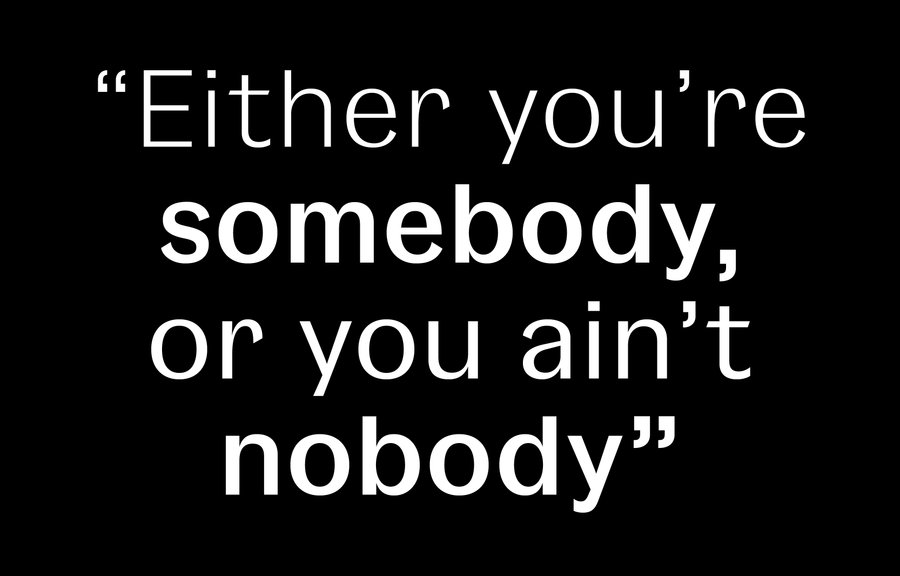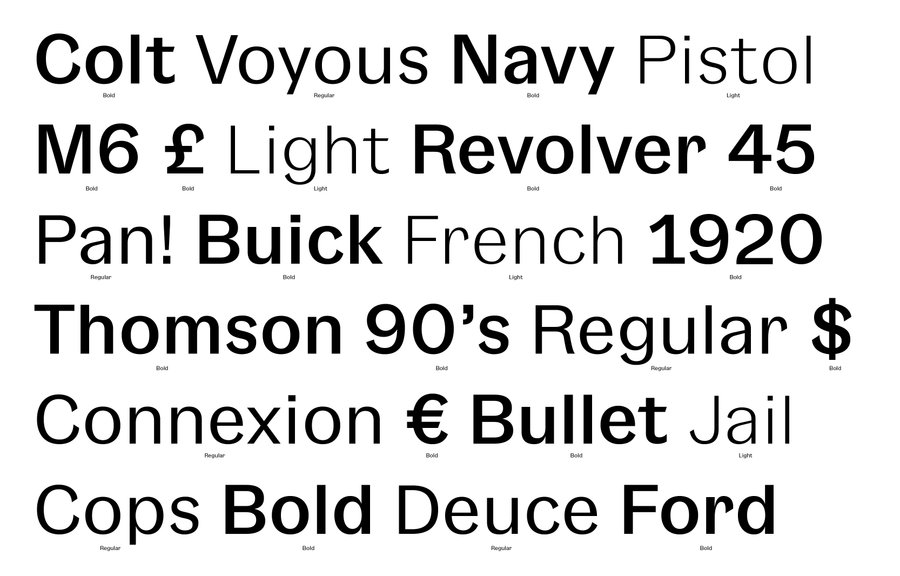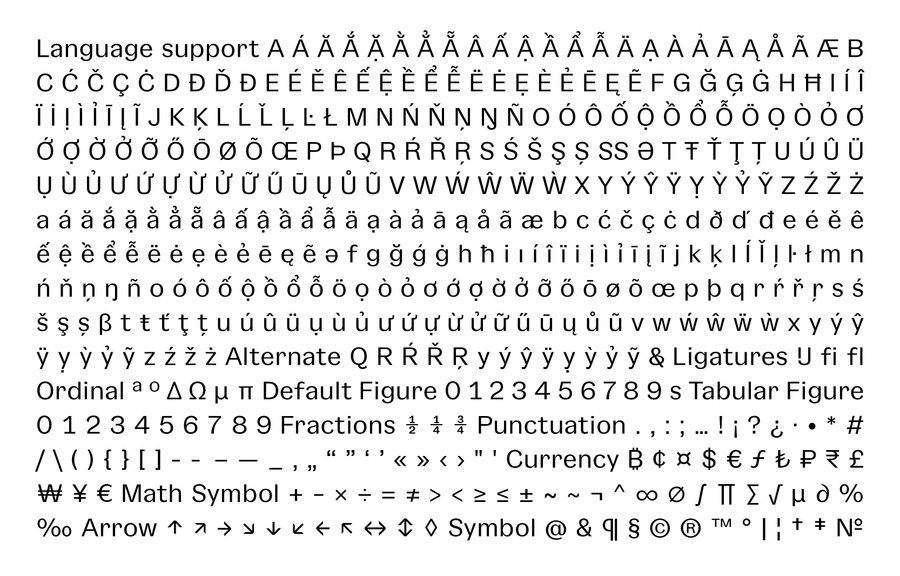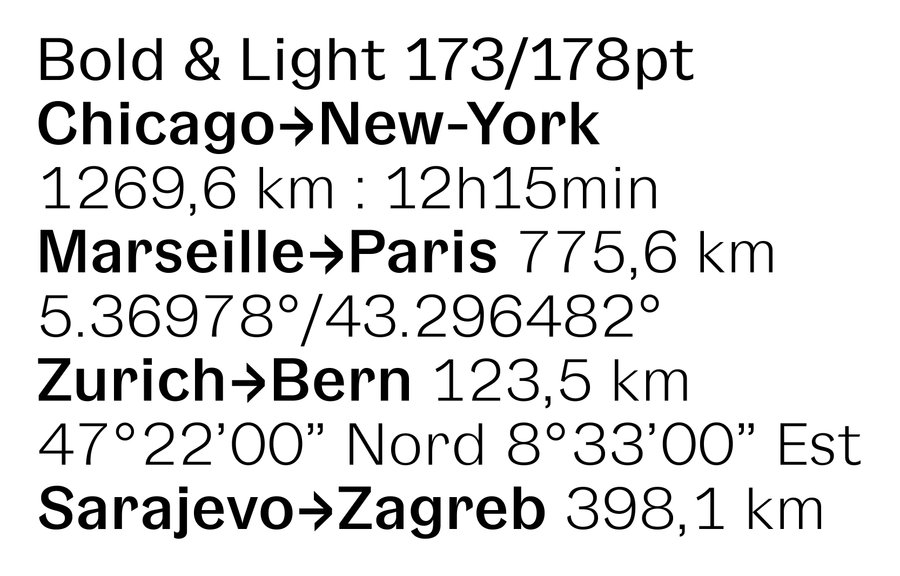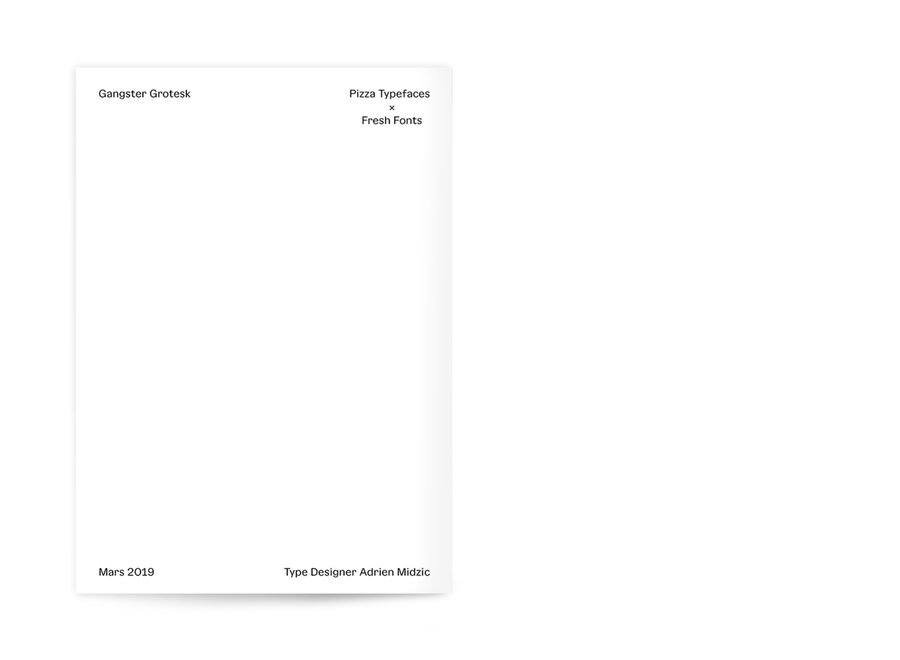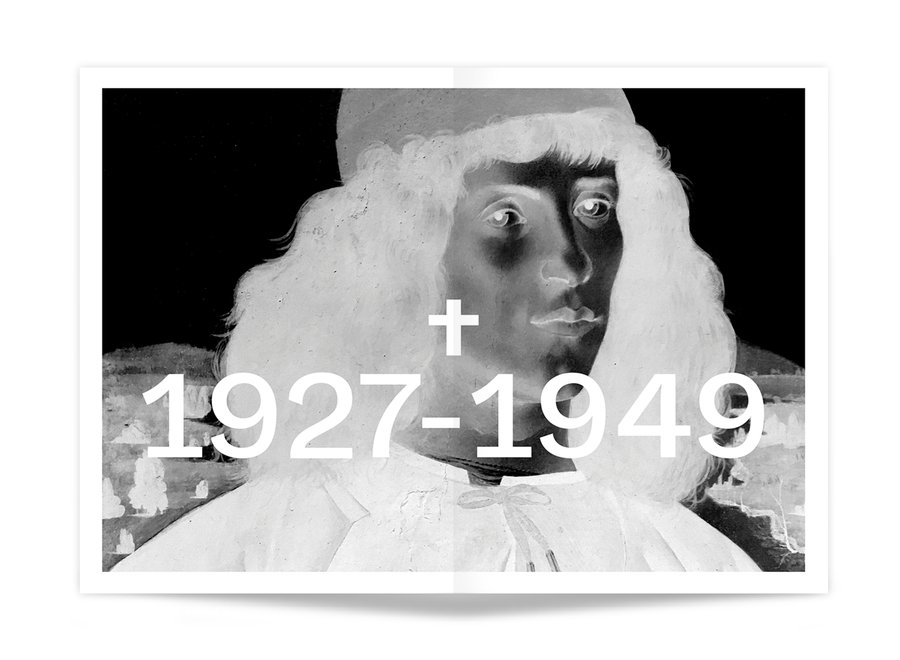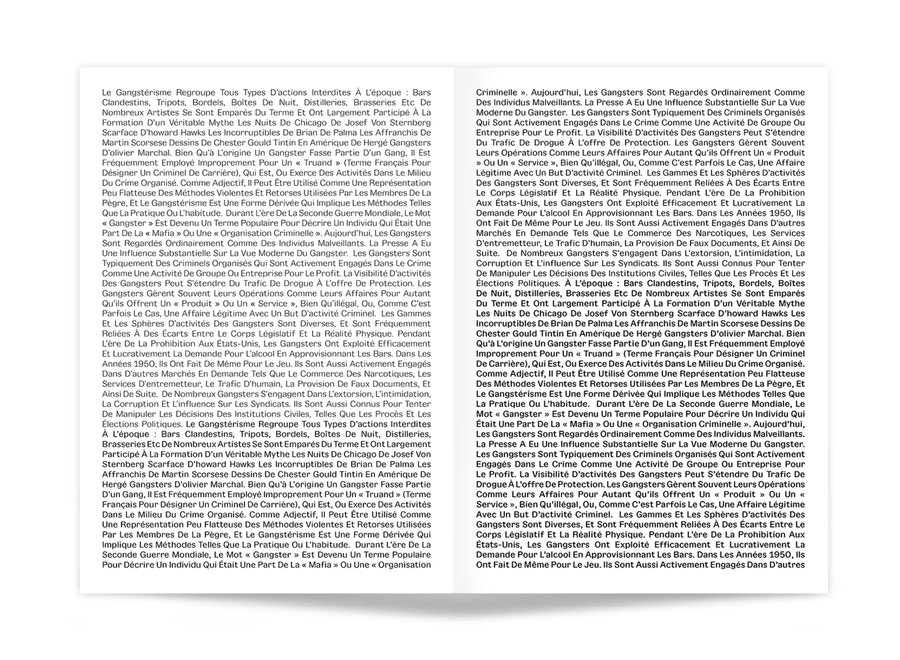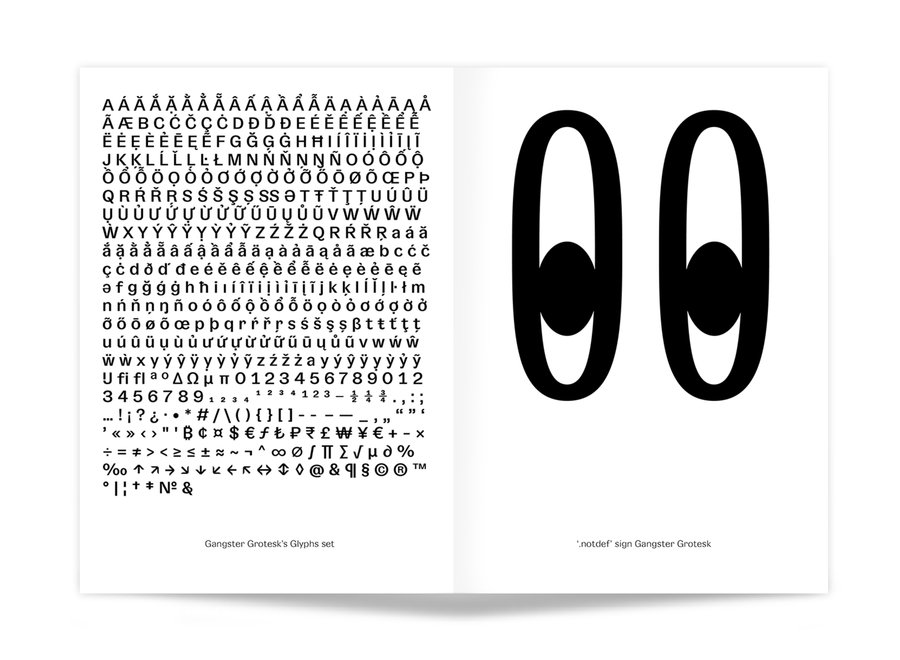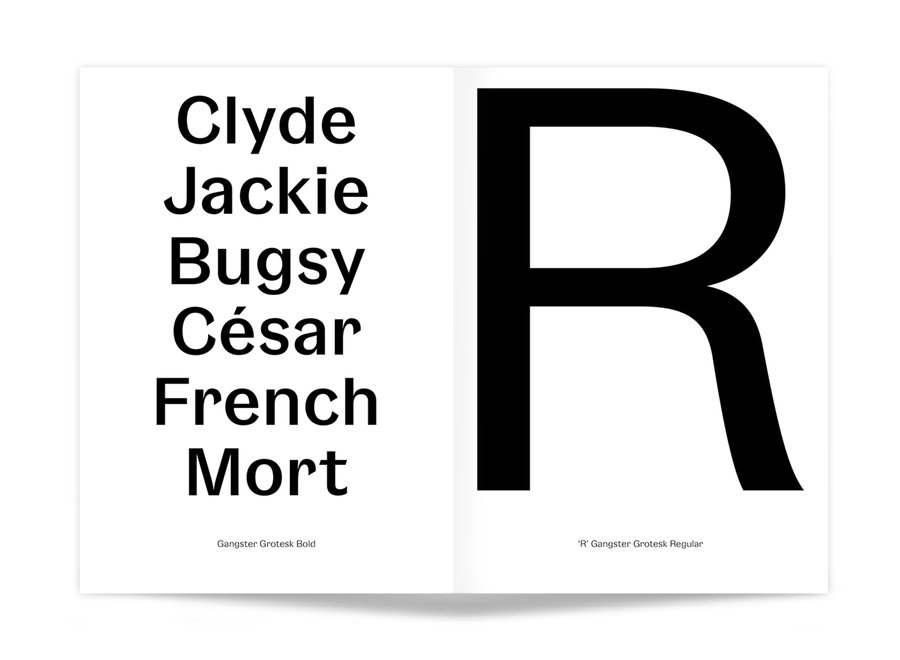
Gansgter Grotesk
Cette famille typographique est une commande Fresh Fonts.
Inspirée des premières "grotesques" des années 1920, Gangster Grotesk est une police de caractères contemporaine qui associe un contraste entre pleins et déliés et des terminaisons fermées. Ces caractéristiques sont simples, reconnaissables et efficaces, prêtant à cette police de caractères un charme prenant toute son ampleur en grande taille et presque invisibles en petites tailles.
La Gangster Grotesk est une alternative aux grotesques existantes et y apporte un nouveau souffle. Cette famille est un outil de travail multifonctionnel conçu pour faire des merveilles, à la fois sur papier et sur écran, notamment pour la création de logos, les identités de marques, les sites Web, les emballages, les affiches et les titres. Sa largeur légèrement condensée est également adaptée aux textes de petite taille.
Ganster Grotesk
Light, Regular et Bold
Adrien Midzic
Adrien imagine, dessine et produit des lettrages originaux pour des exploitations en logo. Graffeur de "formation", il est devenu un excellent typographe et maîtrise parfaitement les rouages de la typographie moderne et y apporte avec subtilité la pointe d'originalité qui leur manquait.